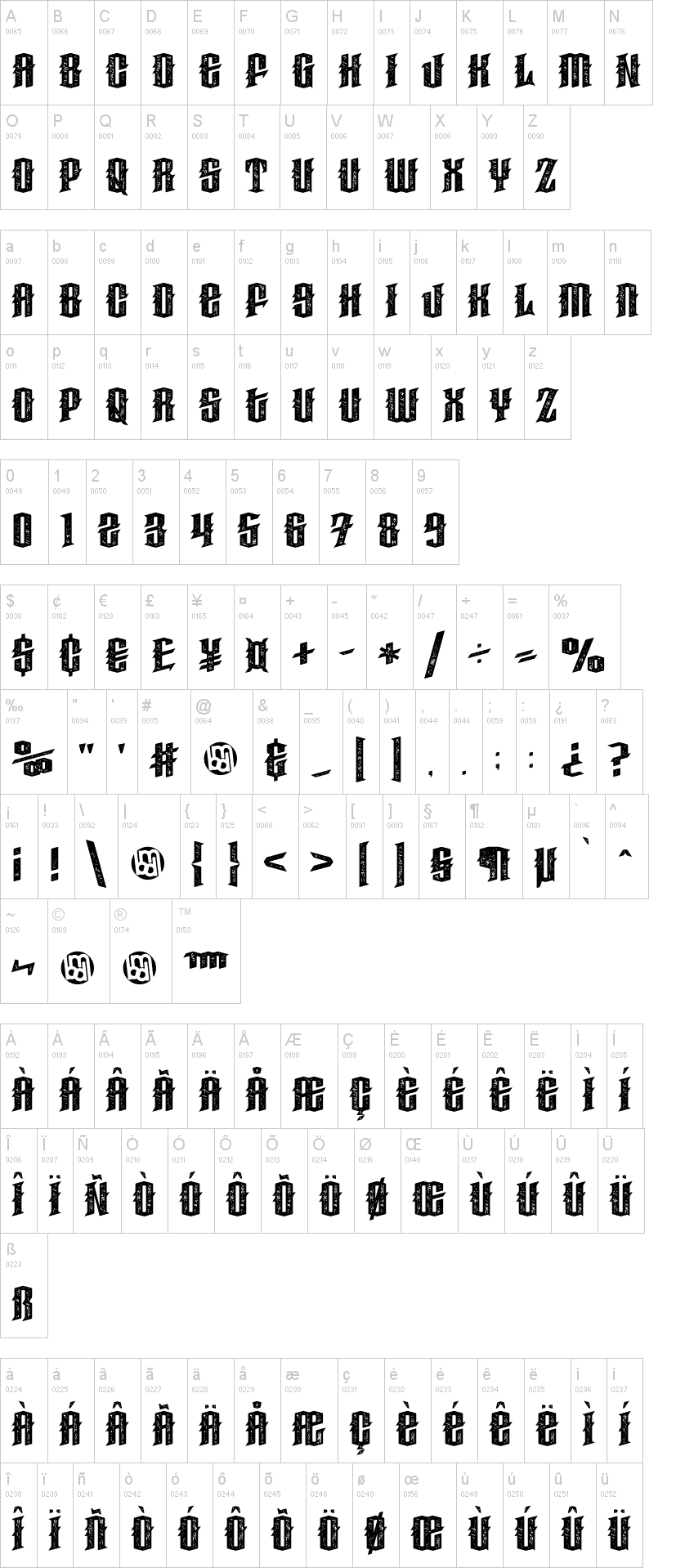
Haunted Woods Corroded是一款英文字体,由K-Type设计,具有独特的折衷风格,结合了古典、街头和古怪的元素,提供了多种字体风格,包括粗体、斜体和带有装饰性的花纹。它具有多种字符,包括大小写字母、数字、符号和特殊符号,可以用于各种应用,如广告、海报、书籍封面、网站等。内容介绍
Haunted Woods Corroded是一款非常不错的手写艺术字体,具有很好的视觉感,适合于文化类的宣传设计、商业类品牌的广告和产品包装设计以及个性化文字排版等较多场景。